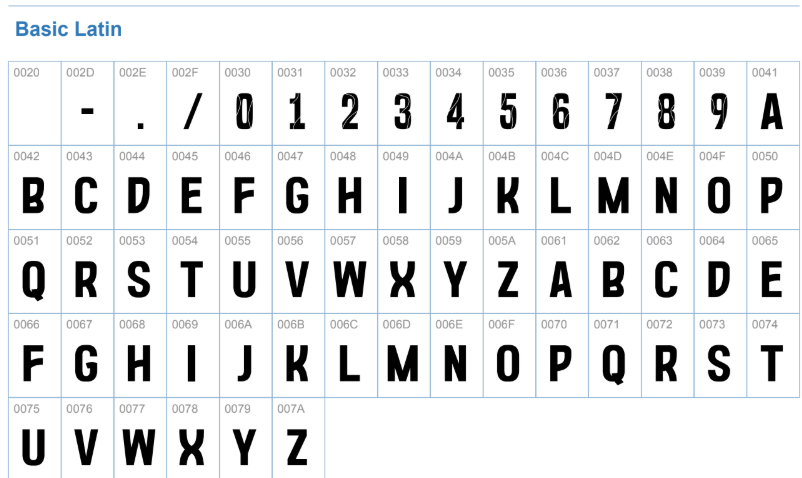
A temporada 2026 do Olympique Lyonnais chega com a missão de recolocar o clube no topo da Ligue 1. Mais do que reforços e tática, o clube aposta na força visual para marcar essa virada de página. A nova identidade vai além do escudo: a tipografia oficial é a espinha dorsal da comunicação, dos uniformes às transmissões.
Para fãs, designers e criadores de conteúdo, ter acesso à fonte do time é o primeiro passo para produzir materiais autênticos. Seja para personalizar uma camisa, criar uma arte para o estádio ou alimentar as redes sociais, o arquivo certo faz toda a diferença. E o modelo 2026 vem carregado de personalidade.
Detalhes técnicos da fonte
O pacote inclui o conjunto completo de caracteres, numerais estilizados e glifos exclusivos que respeitam o manual de marca da temporada.
Estilo visual da tipografia
A fonte do Lyon 2026 abandona o minimalismo discreto e aposta em uma presença forte. Os números têm construção geométrica com cantos levemente chanfrados, criando um aspecto tecnológico e agressivo. As hastes são robustas, garantindo excelente legibilidade nas costas dos jogadores, mesmo nas câmeras abertas da transmissão.
O “9” e o “7” ganharam um desenho particular, com uma “cintura” alta que remete ao movimento ascendente do clube. Não há serifas tradicionais, mas pequenos cortes angulares que dão velocidade à leitura. O contraste entre traços grossos e finos é moderado, pensado para não “estourar” na malha do poliéster dos uniformes.
Aplicação no uniforme
No manto titular, o branco clássico recebe a tipografia em azul marinho, criando um contraste limpo e direto. A versão reserva, predominantemente escura, utiliza os números em prata metálico, quase líquido sob a luz dos refletores.
O terceiro uniforme, um retorno ao grená com faixas verticais douradas, traz os caracteres em dourado fosco, elevando a sensação premium do kit.